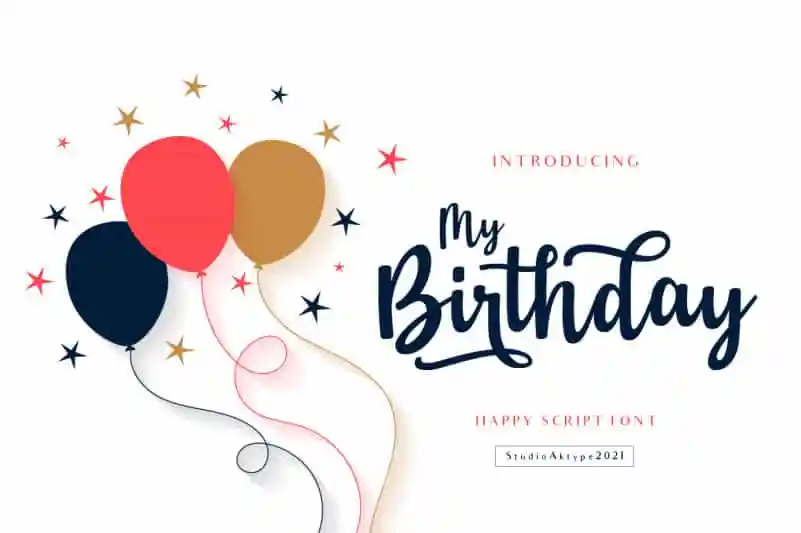
My Birthday Calligraphy Font – Fonte Grátis
My Birthday Calligraphy Font
A fonte My Birthday Calligraphy Font é uma preciosidade para aqueles que buscam adicionar uma pitada única ao seu design editorial ou personalizado. Este elegante conjunto de letras cursivas contém sílabas e caudas frontais e traseiras, criando um efeito profundo e rico em detalhes. Ela foi projetada por studioaktype, com a característica notável de ser PUA (Unicode Precomposed Unicode Alternatives) encoded, o que significa que você pode acessar facilmente todos os símbolos e caudas. Este tipo é ideal para designers que desejam imprimir uma personalidade elegante e autêntica em seus trabalhos. Ele se destaca como a escolha perfeita para gráficos de aniversário ou eventos especiais, mantendo sua identidade única sem comprometer o conforto do leitor. Sua versatilidade faz dele um recurso indispensável para designers atentos à criatividade e aos detalhes finos em suas criações.